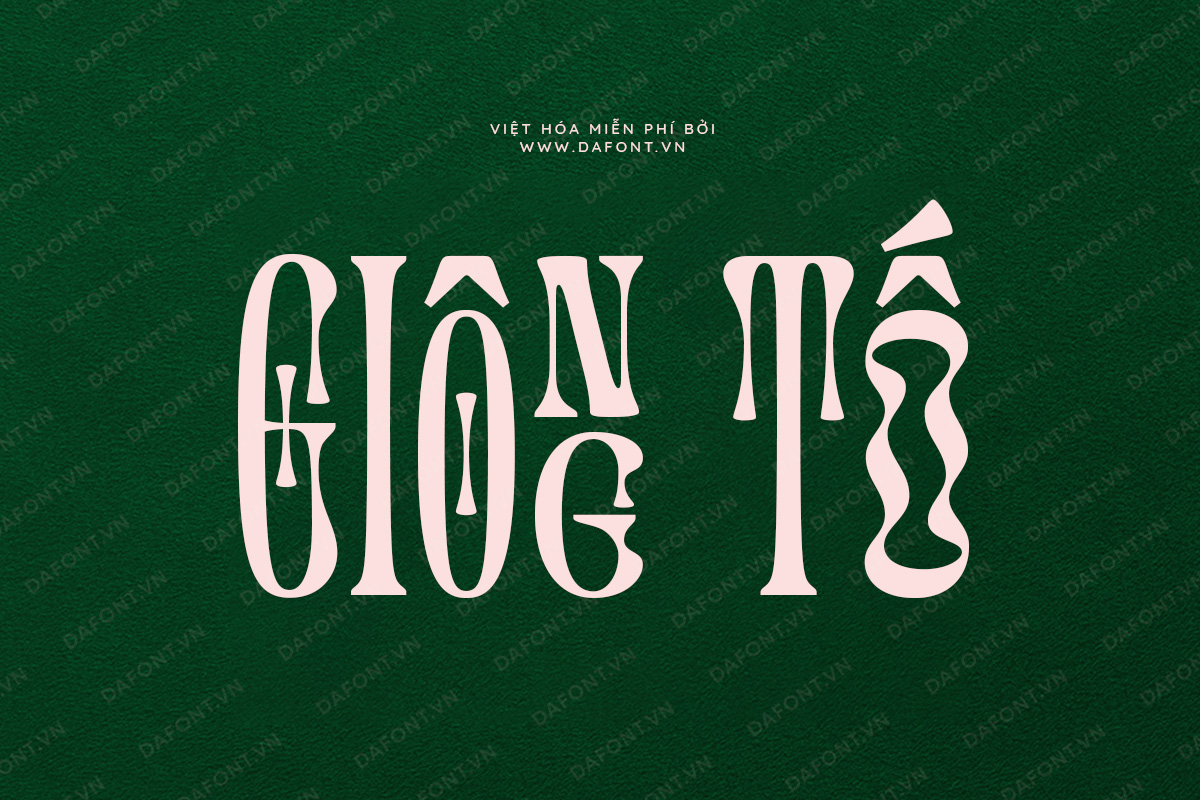
Font việt hóa DFVN Gregonia
DFVN Gregonia – Kiểu chữ đẹp mắt như một nghệ sĩ kể về câu chuyện tình yêu.
Gregonia một kiểu chữ rất đẹp mắt. Các ký tự được tạo ra với độ tương phản tinh tế sẽ trở thành những đặc điểm mạnh mẽ cho các thiết kế của bạn.
Điểm nổi bật là mức độ chi tiết cao được thiết kế để đạt được mức độ căn chỉnh tốt. Gregonia kết hợp giữa sự mềm mại và tinh tế rõ ràng có giá trị thẩm mỹ cao, vừa hiện đại vừa cổ điển và rất thanh lịch. Mặc dù font chữ được dùng để trang trí, nhưng nó vẫn duy trì khả năng đọc tốt.
DFVN Gregonia là lựa chọn tuyệt vời cho thiết kế thiệp mời đám cưới, tiệc sinh nhật, các sự kiện đặc biệt, phù hợp cho tiêu đề sách, tạp chí, blog, thích hợp cho thiết kế poster, quảng cáo, logo, xây dựng thương hiệum sử dụng trong các bài đăng trên mạng xã hội để tăng tính thẩm mỹ và sự tương tác của nội dung.
Gregonia với các nét chữ được thiết kế độc đáo, đẹp và dễ đọc sẽ nâng tầm các dự án sáng tạo của bạn.